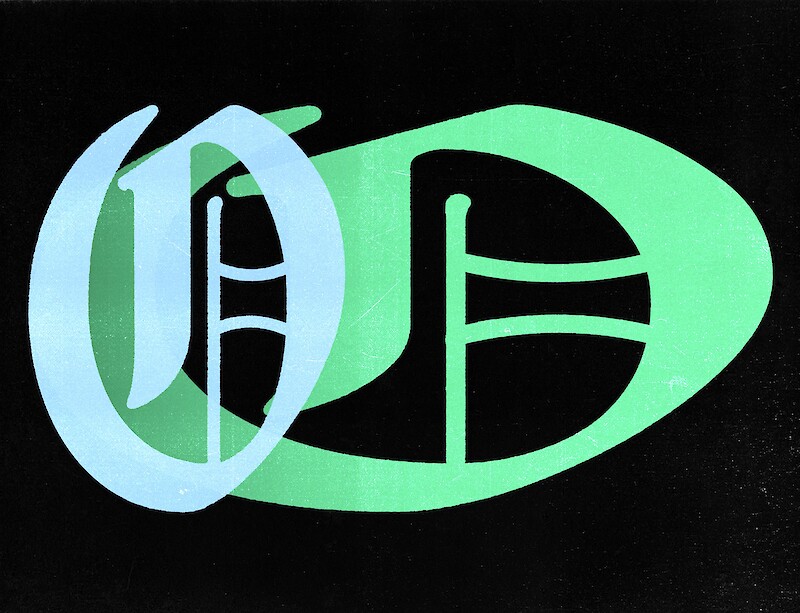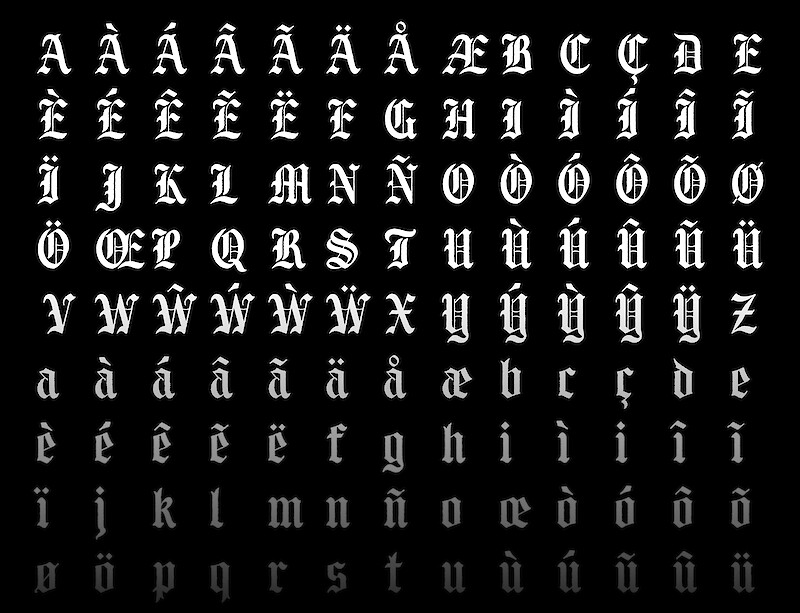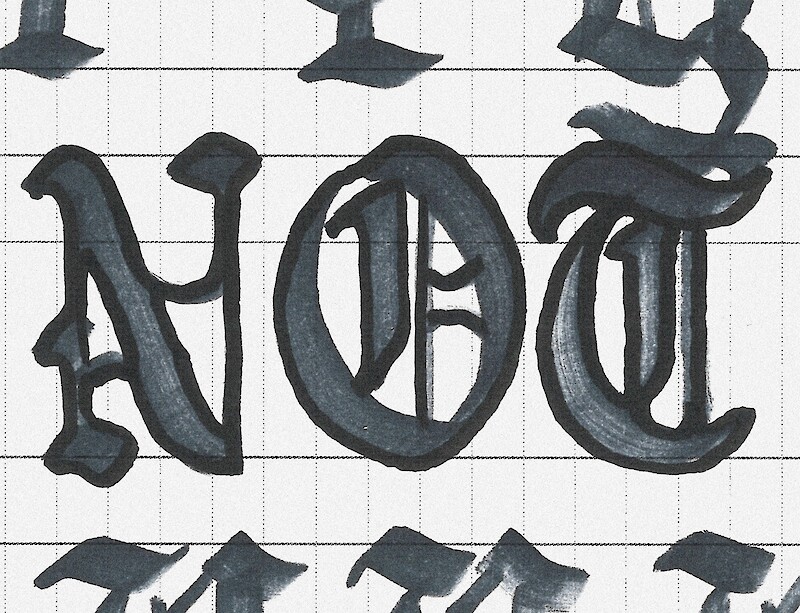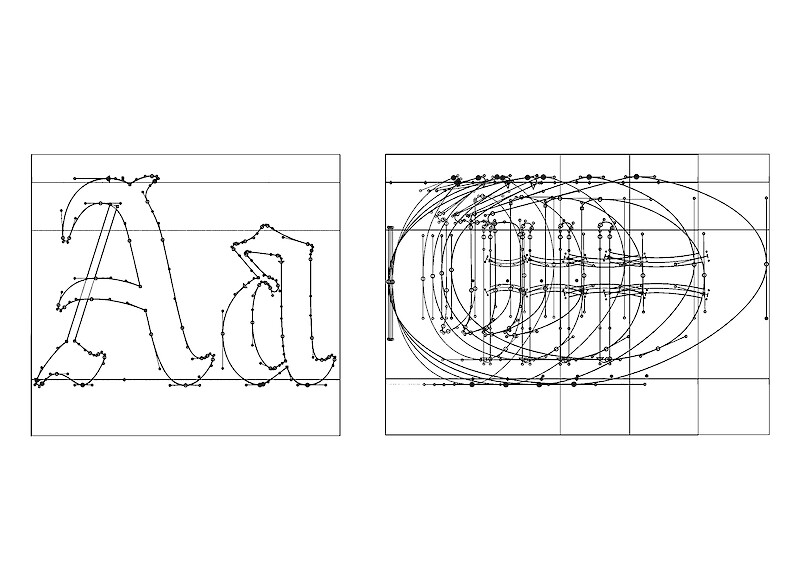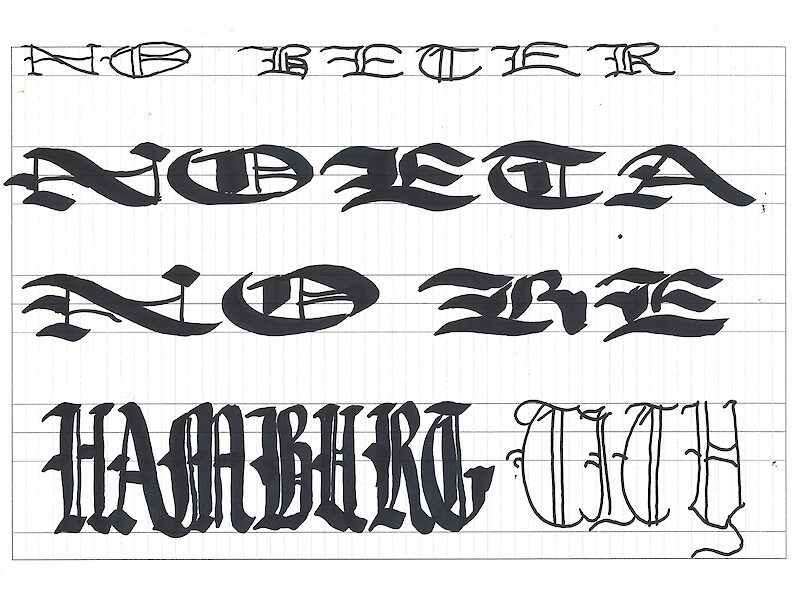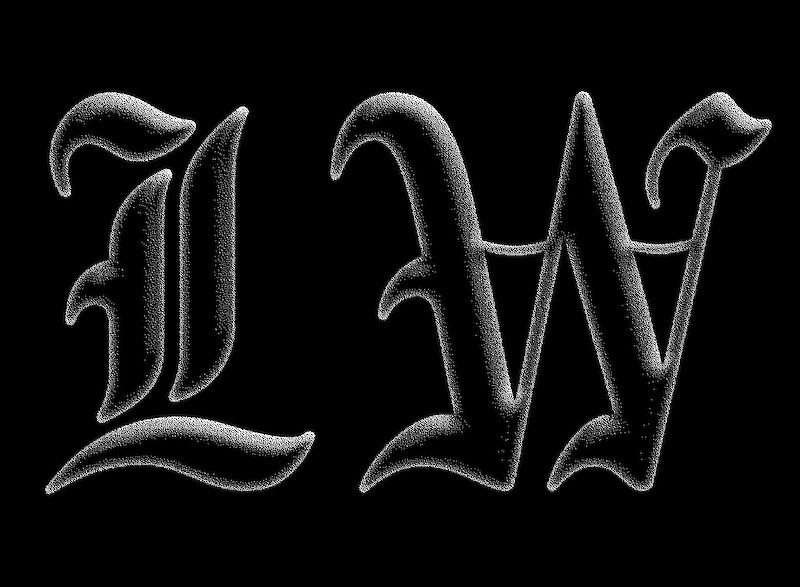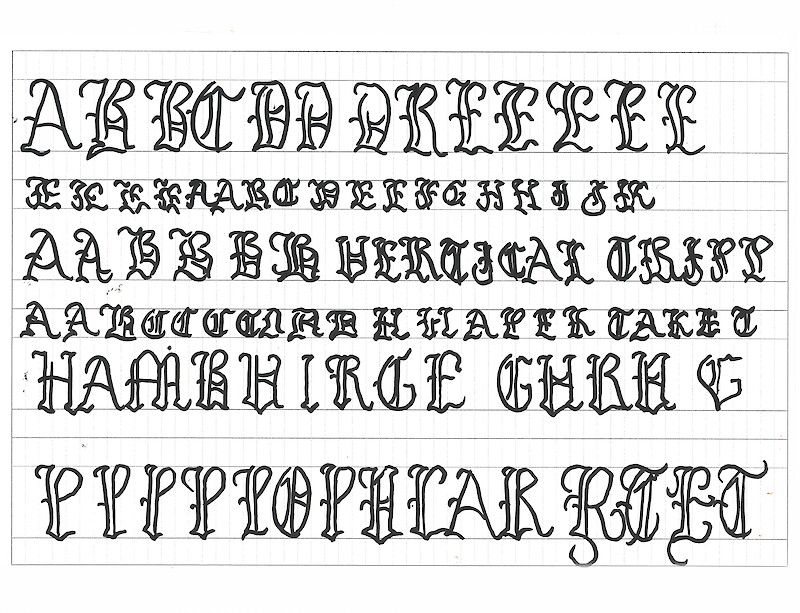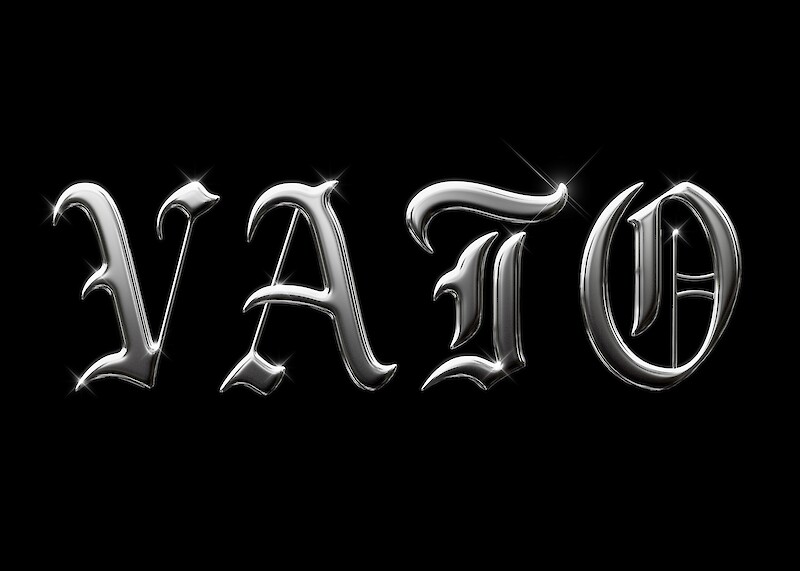
Vato
Die gotische Schrift, einst prägend für Teile Europas, verschwand im 20. Jahrhundert fast vollständig aus der mitteleuropäischen Schriftlandschaft, auch wegen ihrer Verbindung zum Nationalsozialismus. Im Gegensatz dazu blieb sie in Mittelamerika präsent und floss durch den kulturellen Austausch mit afroamerikanischen Gemeinschaften im Süden der USA in den grafischen Ausdruck des Hip-Hops ein. Die Arbeit präsentiert eine neue Interpretation der gotischen Schrift. Inspiriert durch den Hip-Hop bewahrt sie ihren kalligrafischen Charakter und ist heutigen Lesegewohnheiten angepasst.